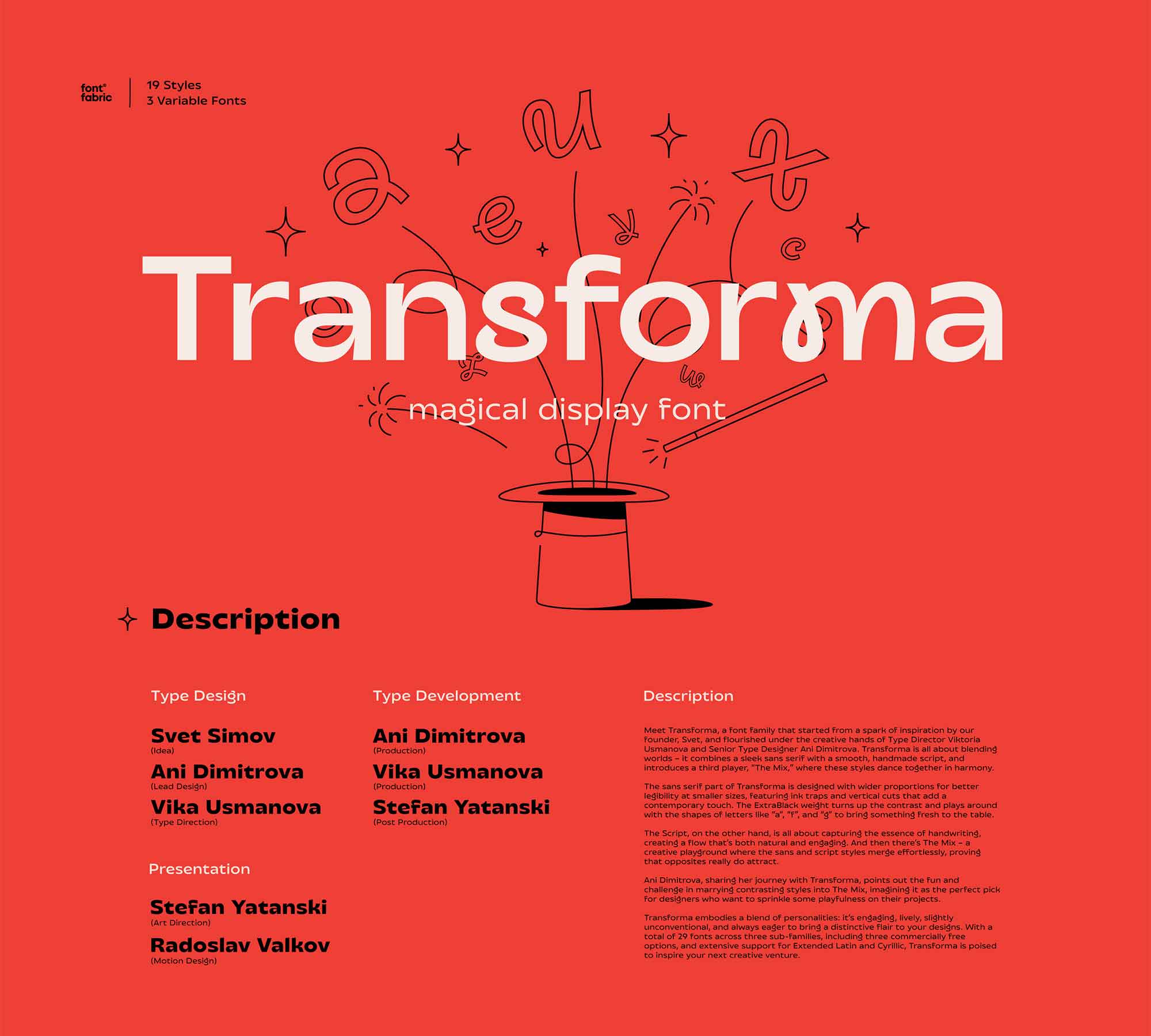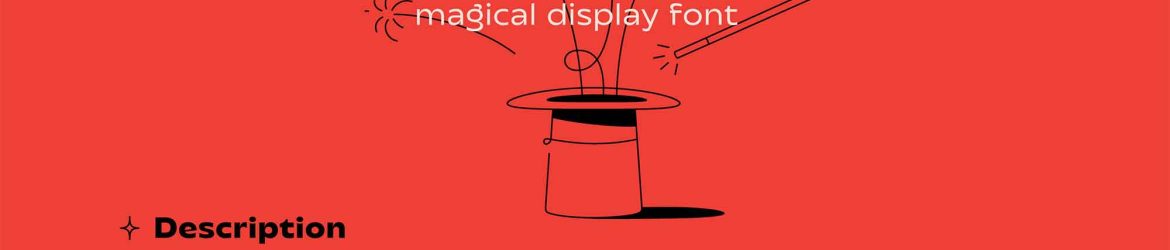
Transforma é uma família de fontes sans-serif que incorpora letras feitas à mão para dentro de seus caracteres, oferecendo uma harmonia perfeita. Este tipo de fonte revoluciona o universo dos designers, tornando o uso da tipografia mais atraente e belo. Com 1058 gílipes de fonte, 22 estilos de fonte e suporte a mais de 100 idiomas, Transforma combina perfeitamente com as mais populares e clássicas fontes. Está preparado para trazer uma nova dimensão à sua arte gráfica, seja no design de logotipos ou em branding. Transforma é uma opção perfeita para os designers que querem inovar e estabelecer uma identidade visual única.